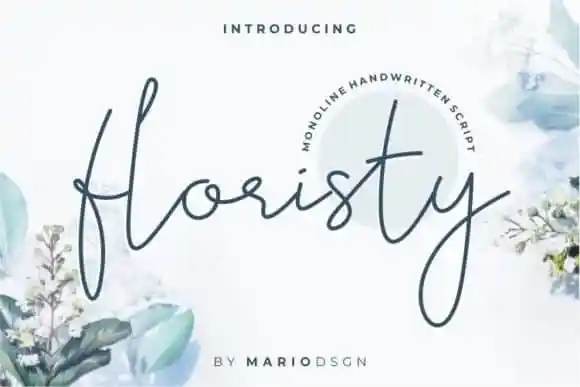
Floristy Handwritten Font – Download Grátis
A Floristy Handwritten Font é uma elegante escolha para designers que valorizam a simplicidade moderna do design calligrafico. Conhecida por seu estilo monoline, essa fonte vem diretamente de MarioDsgn, designer-fontes. Com um toque leve e fluido, Floristy Handwritten captura uma atmosfera clara e sofisticada, tornando-a perfeita para adicionar ao seu próximo design. Este moderno script não apenas brilha em elementos que exijam estilo handwritten, mas também se destaca quando inserido em designs que buscam um ar de minimalismo contemporâneo. Ideal tanto para criações visuais elegantes quanto para interfaces digitais intuitivas, a Floristy Handwritten é uma fonte versátil e moderna perfeita para qualquer designer buscando um toque sofisticado em seu projeto.